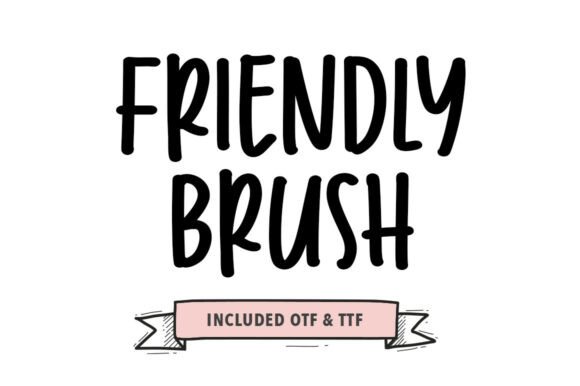
Friendly Brush
適切なデザイン要素を見つけるのは難しい場合がありますが、Friendly Brushは作品を即座に引き立てる優れたコレクションを提供します。
精密に作られたFriendly Brushは、クリーンなベクター、滑らかなタイポグラフィ、そして安心のための商用ライセンスを提供します。
POD(オンデマンド印刷)製品、結婚式の招待状、またはソーシャルメディアのグラフィックを作成している場合でも、Friendly Brushは理想的です。